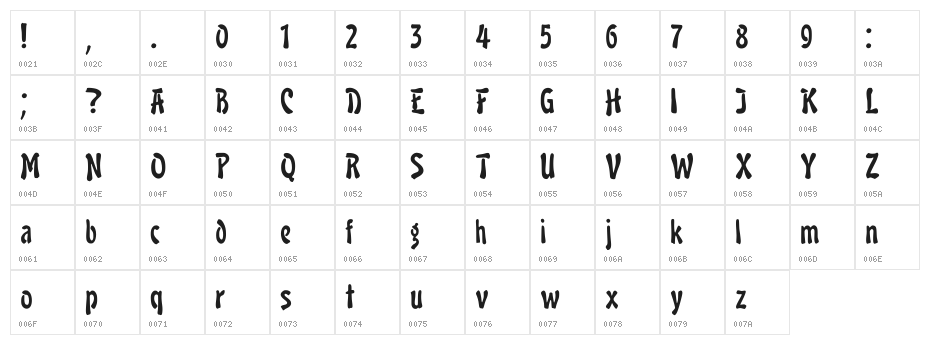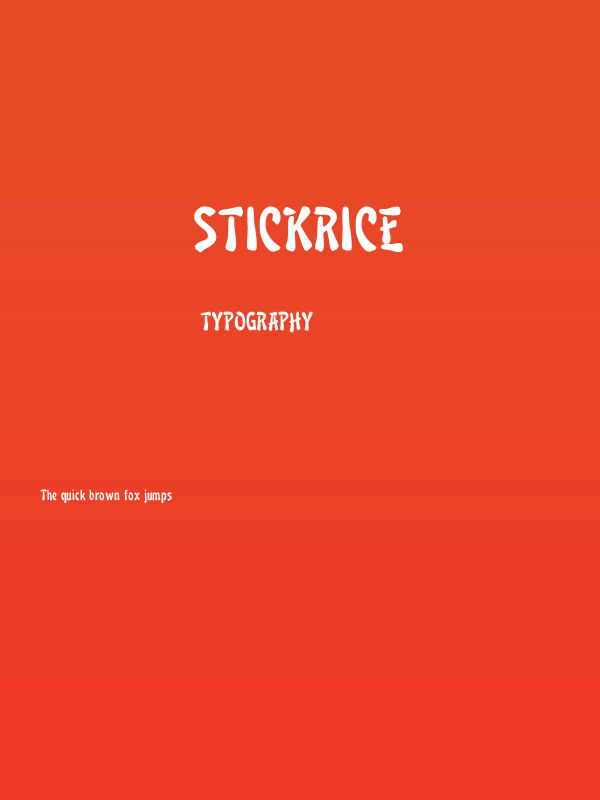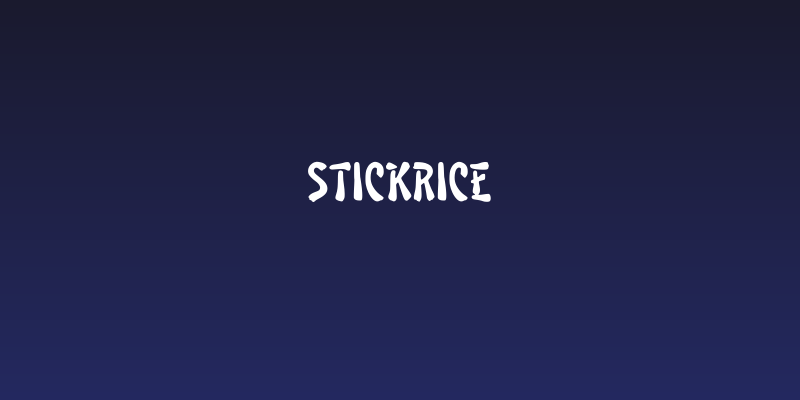
StickRice Font
| Stile generale | Playful, Whimsical, Hand-drawn |
| Progetti proposti | Ideal for children's books, playful branding, party invitations, and creative posters. |